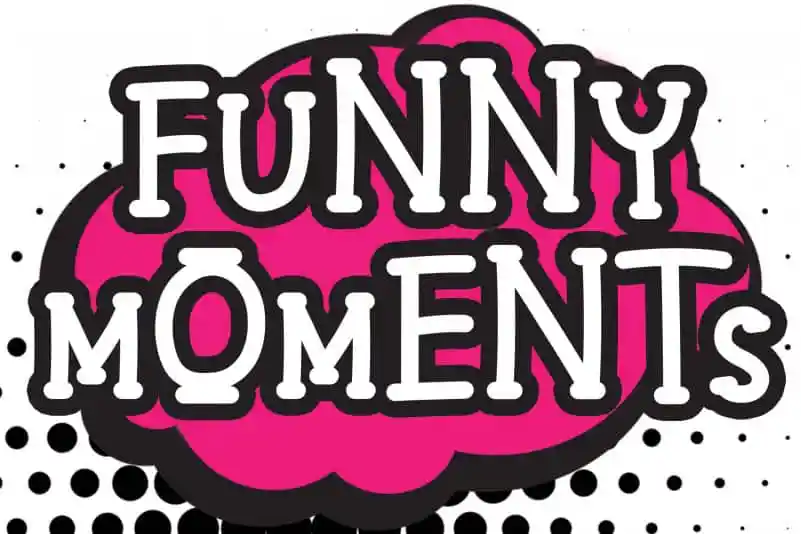
Funny Moments Display Font – Fonte Grátis
Funny Moments Display Font
Essa fonte chamada Funny Moments Display Font é perfeitamente apropriada para quem busca uma experiência visual única e divertida no design do seu site ou aplicativo. Feita pelo designer creativellter, ela traz um toque de criatividade especial para qualquer projeto em que seja usada. Seja para criar menus informativos com destaque em sua plataforma digital ou adicionar um toque de humor a seus designs gráficos interativos, esta fonte garantirá uma experiência memorável e divertida para os usuários. Imagine o sorriso no rosto do seu público ao ler textos chiques e coloridos em suas aplicações; Funny Moments Display Font faz isso possível. E como ela se destaca entre outras fontes de display é por ser um pouco mais brincalhona, capaz de criar experiências memoráveis sem perder a estética elegante que tanto amamos no design digital.